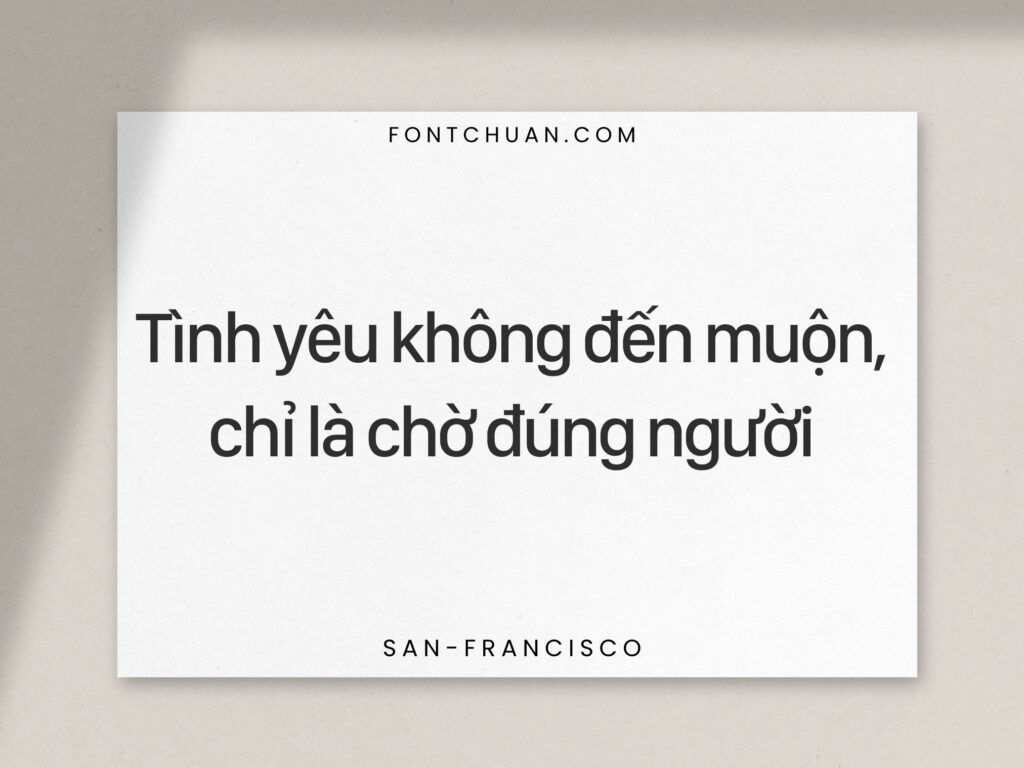
Font San Francisco Trọn Bộ
Tác giả Font: Apple
San Francisco là bộ font sans-serif hiện đại do Apple Inc. phát triển, lần đầu được giới thiệu vào năm 2014 như một phần trong việc nâng cấp hệ thống hiển thị chữ cho các thiết bị Apple. Đây là font chữ chính thức của iOS, macOS, watchOS và tvOS, với các biến thể tiêu biểu như SF Pro, SF Compact và SF Mono – một Font Monospace dành riêng cho lập trình viên. Nhờ tính rõ ràng, hiện đại và tối ưu cho môi trường số, San Francisco còn được coi là một Font chữ công nghệ tiêu biểu trong thế giới thiết kế, đồng thời có thể ứng dụng linh hoạt như một Font chữ bất động sản khi cần thể hiện sự chuyên nghiệp, tin cậy và tính thẩm mỹ trong các tài liệu, ấn phẩm truyền thông của doanh nghiệp. Font này được thiết kế đặc biệt để tối ưu khả năng đọc trên mọi kích thước màn hình, từ điện thoại, đồng hồ thông minh cho tới máy tính. San Francisco hỗ trợ tiếng Việt và hơn 150 ngôn ngữ khác, được thành viên của Font Chuẩn sưu tầm và đăng tải, nhằm phục vụ nhu cầu thiết kế nhất quán với hệ sinh thái Apple của người dùng Việt.
San Francisco có thiết kế hình học rõ ràng, độ cao chữ (x-height) lớn giúp dễ đọc, các phiên bản font còn hỗ trợ thay đổi quang học theo cỡ chữ. SF Pro mang lại trải nghiệm liền mạch trong giao diện người dùng, SF Compact được tối ưu cho màn hình nhỏ như Apple Watch, còn SF Mono dành riêng cho lập trình viên. Font này lý tưởng cho thiết kế giao diện, app, trang web, slide thuyết trình, tài liệu kỹ thuật. Ngành nghề phù hợp gồm công nghệ, giáo dục, quảng cáo và bất động sản. Ngoài ra, San Francisco cũng phù hợp với các sự kiện như lễ hội, sinh nhật, ngày Nhà giáo và Valentine.